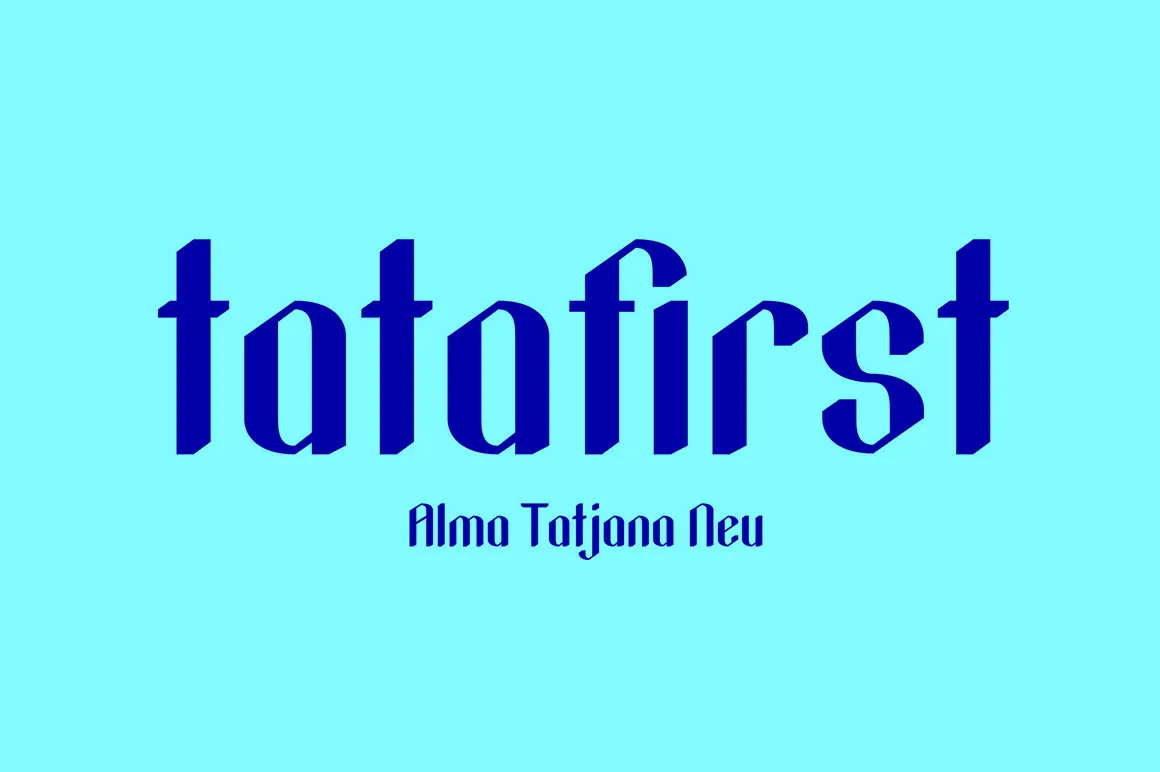
A Tatafirst Font é uma opção ideal para designers buscando personalidade e destaque em seus projetos. Esta fonte display foi desenvolvida pelo designer Hamilton, que partilhou com o mundo os benefícios de sua criatividade. Seja para criar headlines impactantes, logotipos exclusivos ou até mesmo ilustrações infantis, a Tatafirst Font se adapta perfeitamente. Ideal não só para embalagens originais e materiais de leitura infantil, mas também para designs que exigem uma pitada de originalidade em camisas personalizadas. Sua simplicidade e destaque garantem que seja usada com sucesso em qualquer aplicação visual desejada. Se você está procurando por uma fonte display única que pode destacar sua marca ou design, a Tatafirst Font provavelmente é o item perfeito para seu estoque de recursos gráficos.